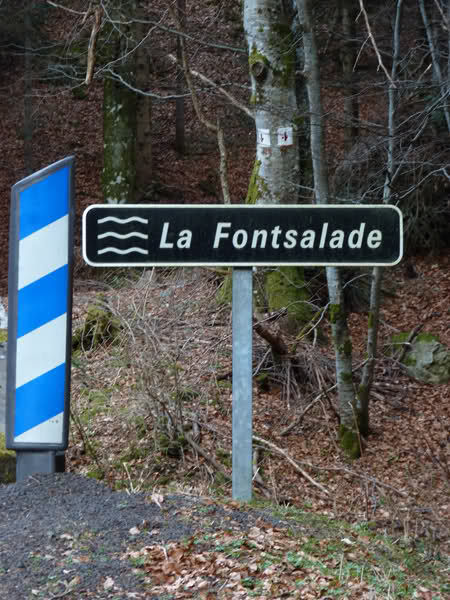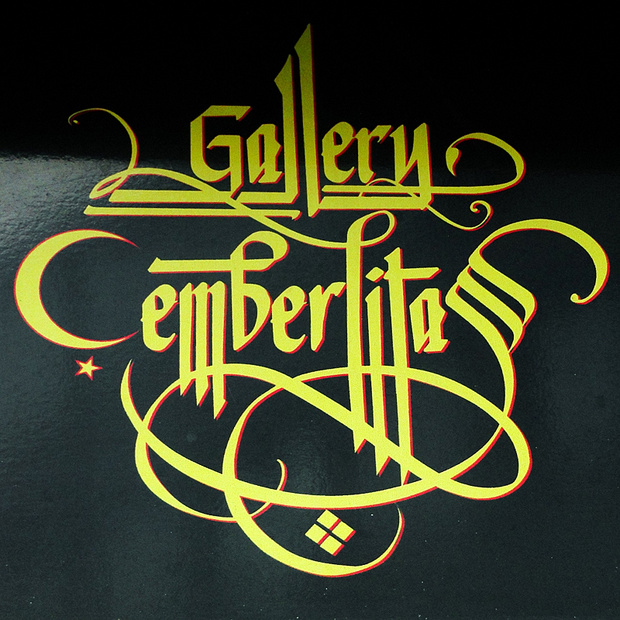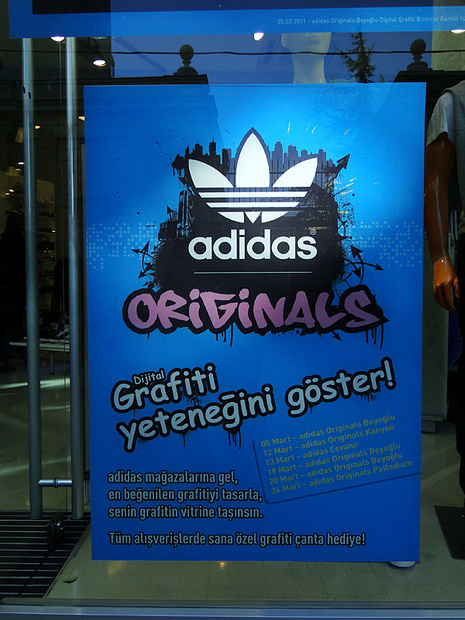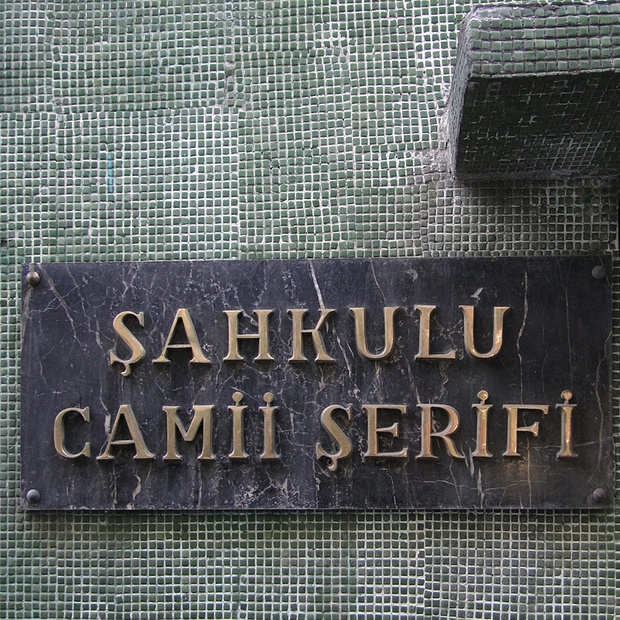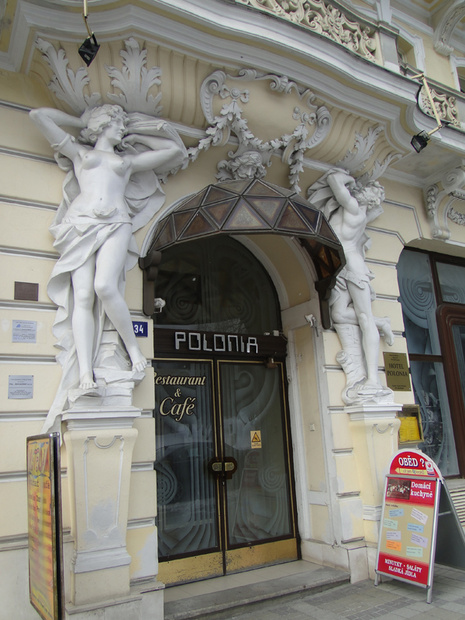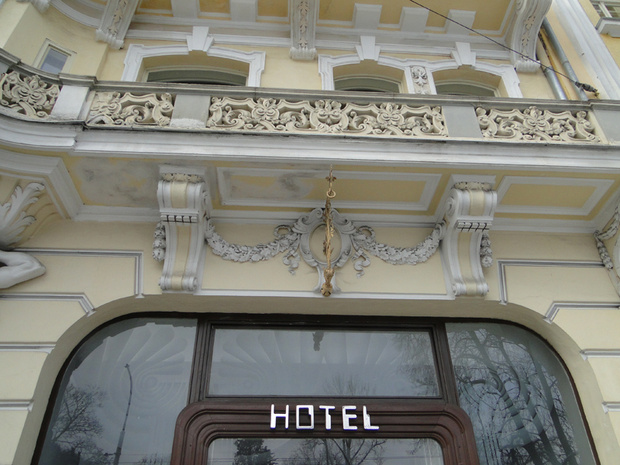
Aber im Ernst, ist schon ein schönes Bandwurmwort auf so einer Verpackung, oder? Normalerweise würde ich da eher so ein Kauderwelsch erwarten wie »nail polish remover pad« Oder »Nagellack Entferner Tuch« oder NagellackEntfernerTuch«. ;-) Ich habe mich jedenfalls beim Lesen drüber gefreut.
Fragt mich bloooß nicht, was genau ich da umgstellt habe!
Aber hübsch war's ja :-)
Du måste ta bort fontcachen kommer den igen visas korrekt.
ein paar schnappschüsse aus istanbul:
interessante anwendung der comic sans, keine ahnung ob das offiziell von adidas abgesegnet wurde oder ob die nur die vordrucke mit dem logo geliefert haben. es hing jedenfalls in einem adidas store
schöner name für eine moschee
die gallery von Ömer Başdağ bei dem man sich seinen namen kalligrafisch schreiben lassen konnte, was ich natürlich getan habe. leider ist seine webseite www.hatyazi.com geparkt.
gesehen in marienbad, tschechien.
hier dachte sich der beschrifter sicherlich mal etwas modenen schick an die
alten häuser anzubringen kann nicht schaden. :neenee:
jepp, ich konnts auch kaum fassen und war auch richtig schockiert. ich kann mir aber vorstellen das den russen (die dort anscheinend 95 % der touristen ausmachen) das richtig gut gefällt ;)
die tschechen haben aber eh einen sehr komischen geschmack sachen zu mixen, ich muss unbedingt mal der wegleitesysteme (für öffentlich einrichtungen, firmen etc.) fotografieren, da bekommste 'nen kollaps.
interessante anwendung der comic sans, keine ahnung ob das offiziell von adidas abgesegnet wurde oder ob die nur die vordrucke mit dem logo geliefert haben. es hing jedenfalls in einem adidas store
Ich frage mich, ob das Schild überhaupt von Türken gestaltet wurde – oder in irgendeiner fernen Agentur. Ich bin jedenfalls über das ḡ (g-Macron) gestolpert, das es im Türkischen gar nicht gibt. Die Comis Sans MS scheint über gar kein ḡ zu verfügen. Sowohl bei meiner Comic Sans als auch der bei MyFonts sieht das im Türkischen verwendete ğ (g-Breve) genau so aus wie man es erwartet: mit einem klar schüsselförmigen Akzent. Verdächtig ist auch, dass ḡ und ğ bunt gemischt im Text unter dem Slogan vorkommen.
Gestern bei einem Ausflug in die ollen Vulkanberge (Auvergne) hab ich dies – für alle Typofreunde – gefunden:
Sehr schön :-P
Wow, echt toll.
Viertel neun? Wo spricht man derart in Rätseln? ;-)
Ich kenne das aus Nordhessen und Thüringen, wenn ich nicht irre … :-)
Ja, ich kenn das schon, auch meine fränkische Verwandtschaft sagt das :shock: … ich muss trotzdem jedes mal überlegen was sie denn meinen. 5.15 Uhr als Viertel sechs zu bezeichnen ist einfach ungewohnt, zumal in Bayern die Uhren eh nicht so genau gehen und man zu 5.15 Uhr eher ’s ist grad fünf vorbei sagt. Ist halt näher an der Fünf als an der Sechs.